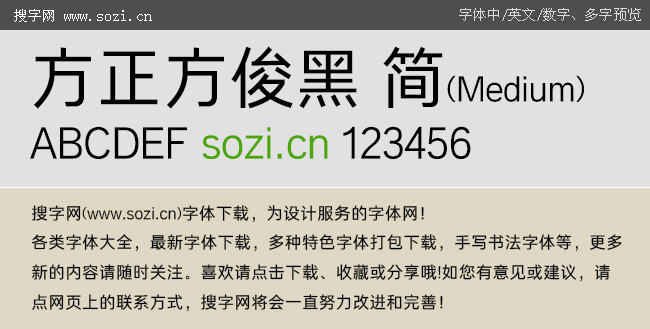
方正方俊黑-簡(jiǎn)Medium
搜字網(wǎng)提供一款方正方俊黑簡(jiǎn)體中文字體下載,方正方俊黑字體是一款由方正字庫(kù)最新開(kāi)發(fā)的字體,這款字體是在方正俊黑字體的基礎(chǔ)上設(shè)計(jì)而成的,字體整體看上去簡(jiǎn)靜優(yōu)雅,筆形簡(jiǎn)練,具有很好的視覺(jué)效果,適合應(yīng)用于包裝設(shè)計(jì)、平面設(shè)計(jì)、網(wǎng)頁(yè)設(shè)計(jì)等應(yīng)用。